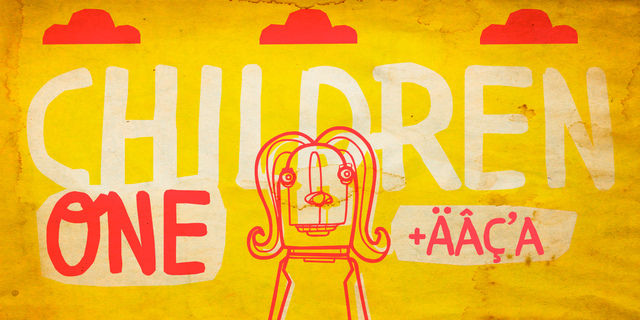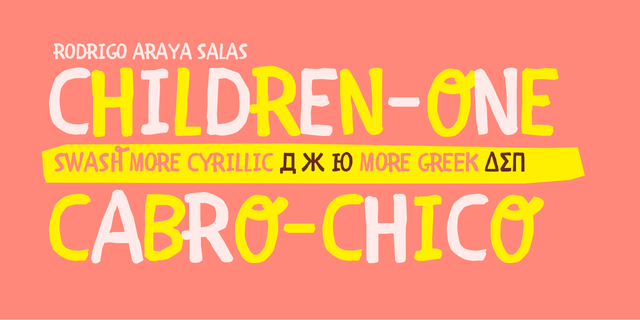
Children One – неформальный рукописный шрифт с игривым и добродушным настроением с поддержкой множества европейских языков, а также кириллицы и греческого. Этот шрифт имеет богатые возможности в виде альтернативных глифов, росчерков и редких лигатур. Шрифт Children One разработал Родриго Арая Салас в 2014 году.
добрый, добродушный, уличный, доброжелательный, бытовой, крафтовый, неформальный, мультяшный, ручной, наивный, рукотворный, кустарный, самодельный, высокий, оригинальный, живой, характерный, игривый, заметный, домашний, выразительный, неряшливый, подвижный, непоседливый, ремесленный, забавный, милый, интересный, творческий, симпатичный, артизанальный, природный, натуральный, небрежный, вернакулярный, зимний, снежный